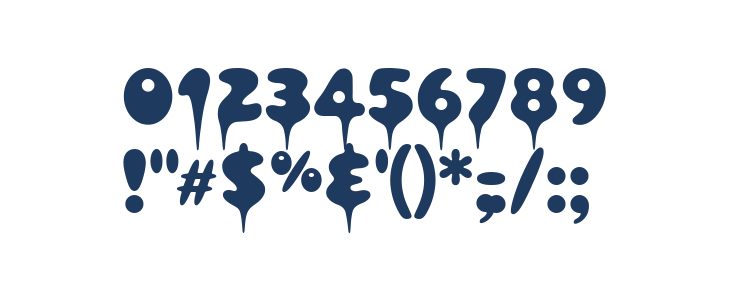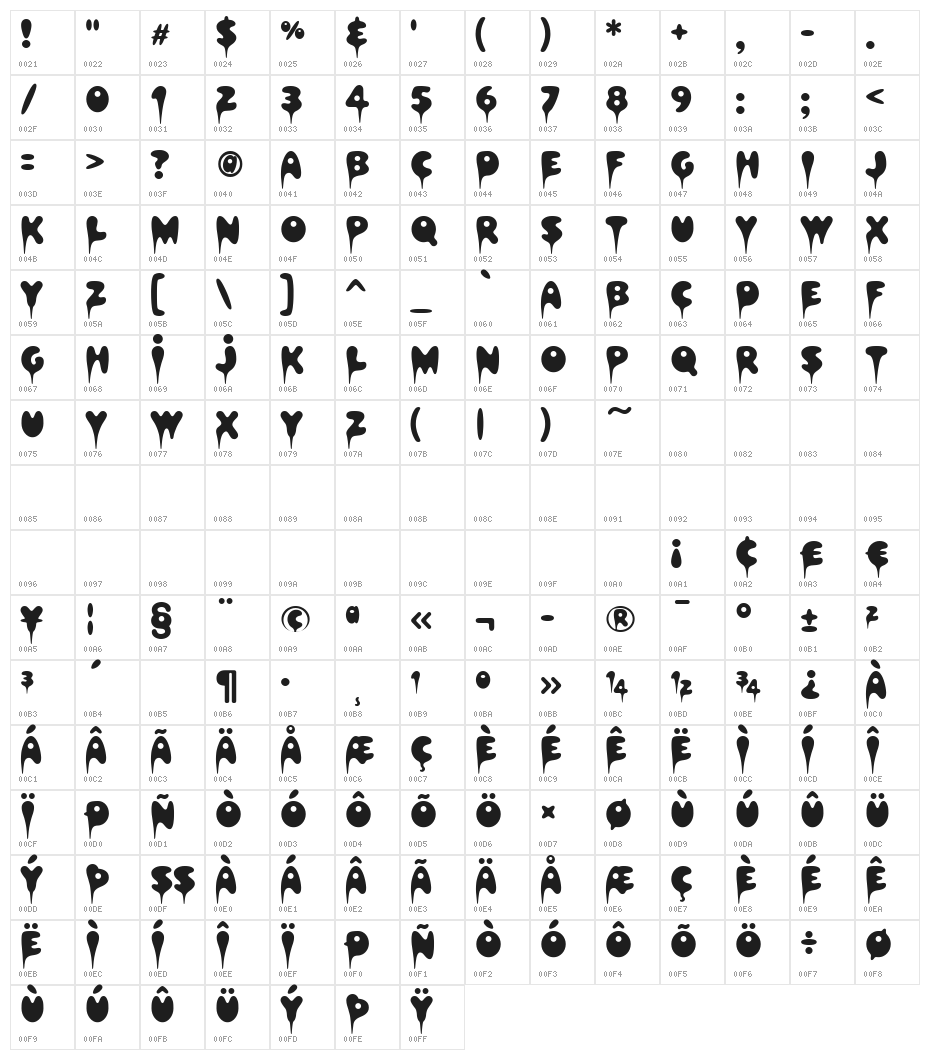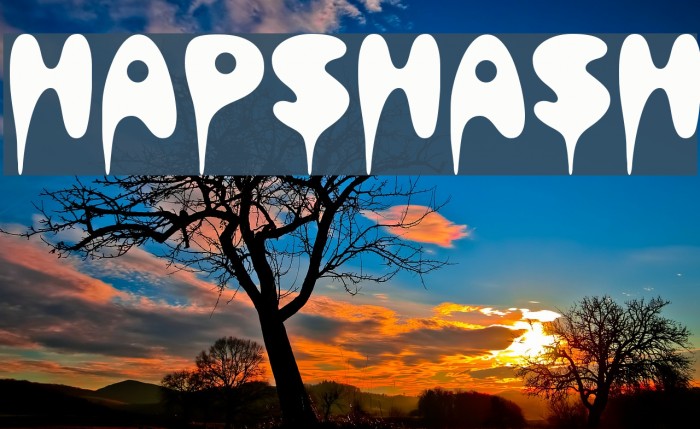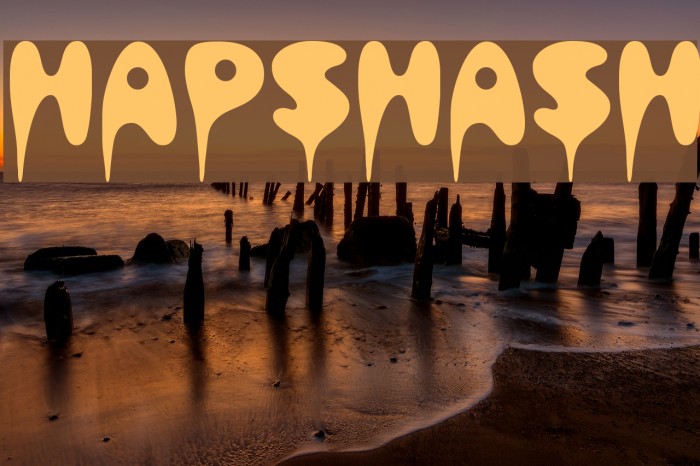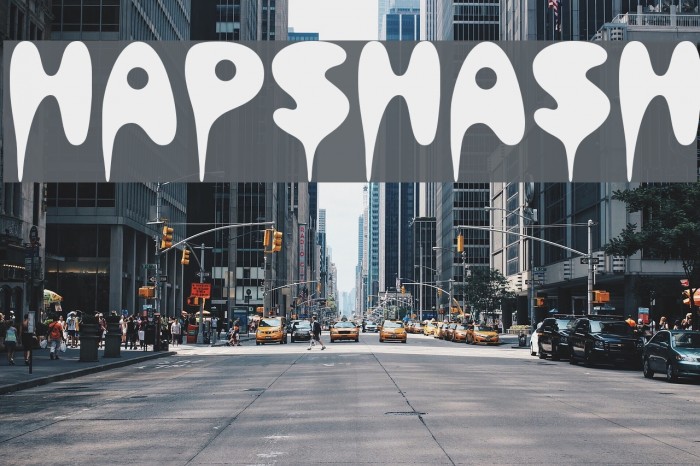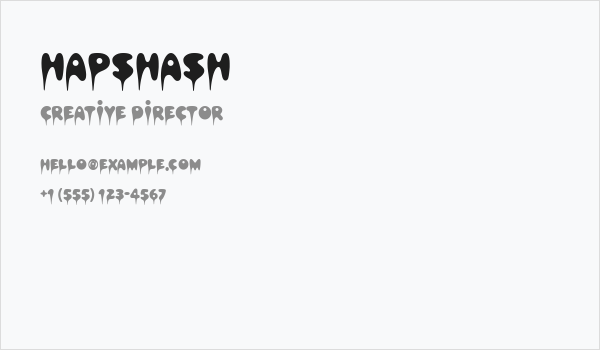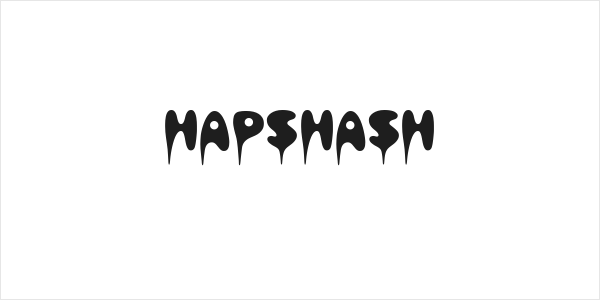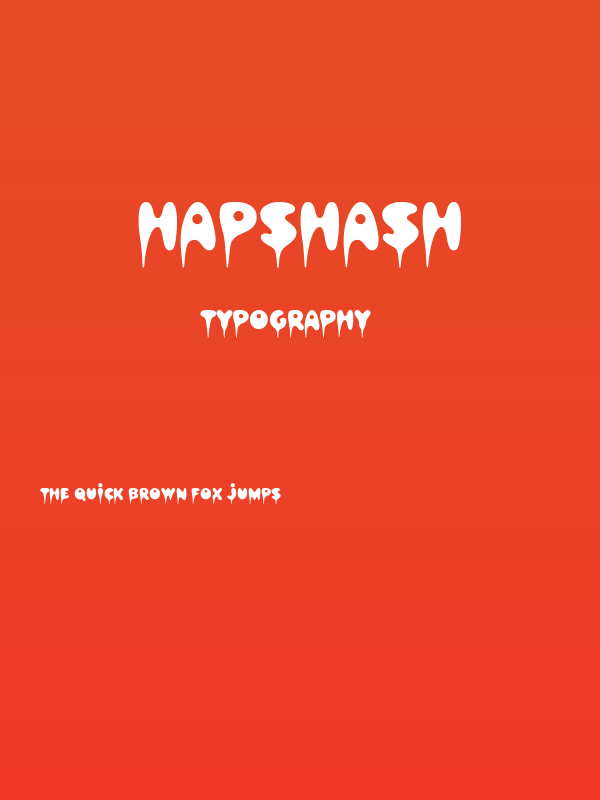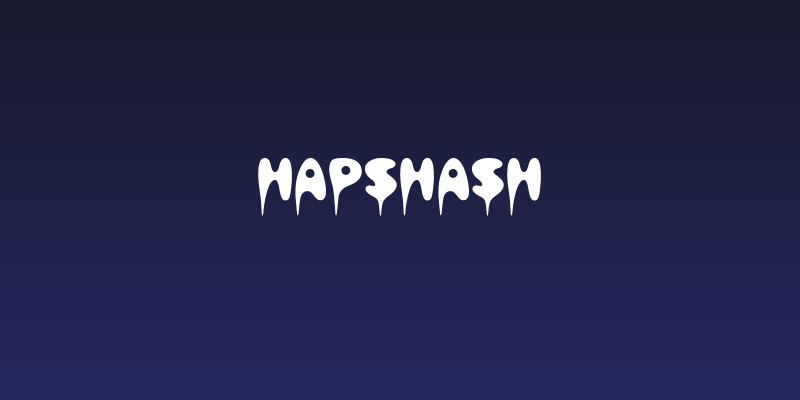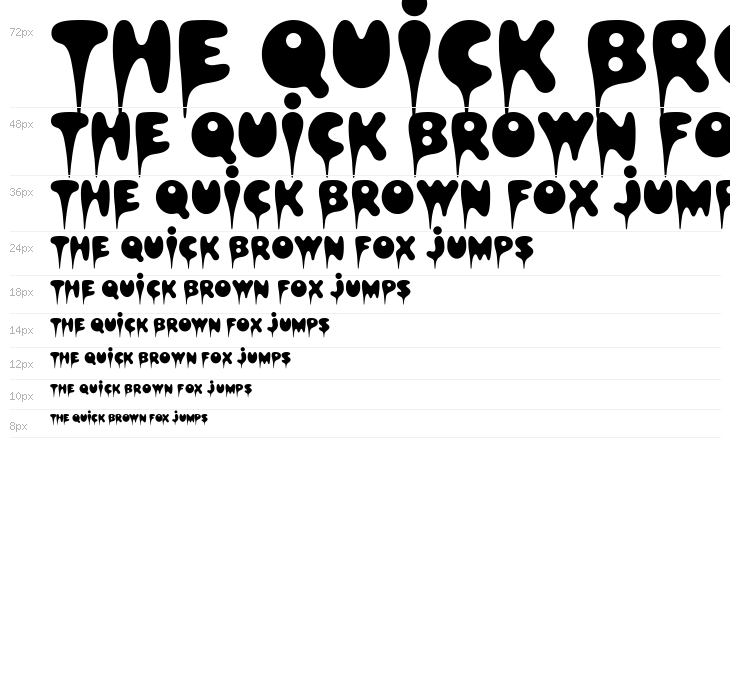
Hapshash Font
| Caso d'uso | Logos, Posters, Headlines |
| Progetti proposti | Ideal for Halloween-themed designs, music posters, or any project needing a bold, eye-catching aesthetic. |